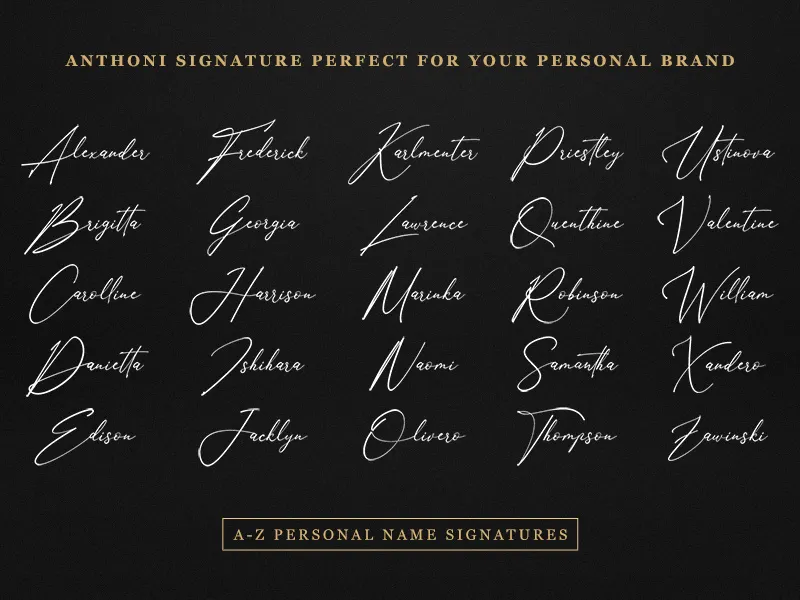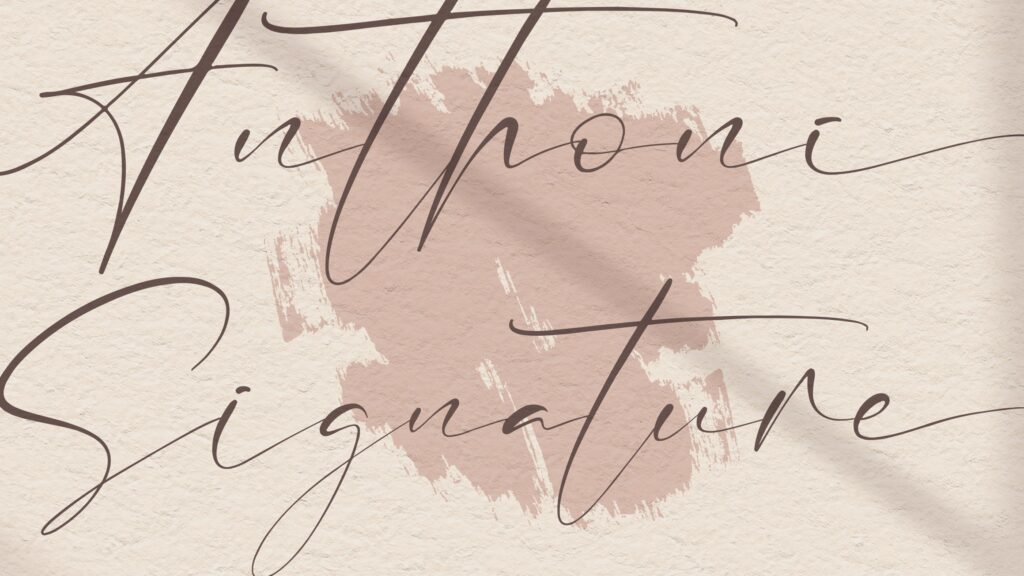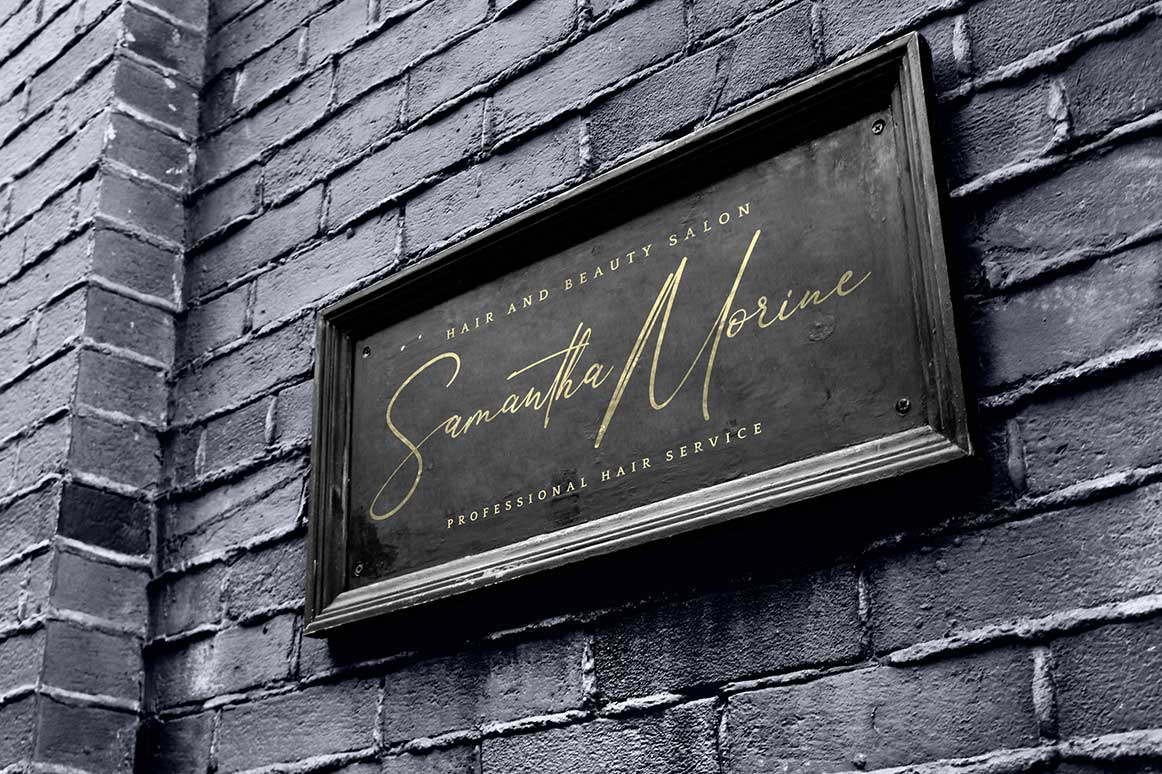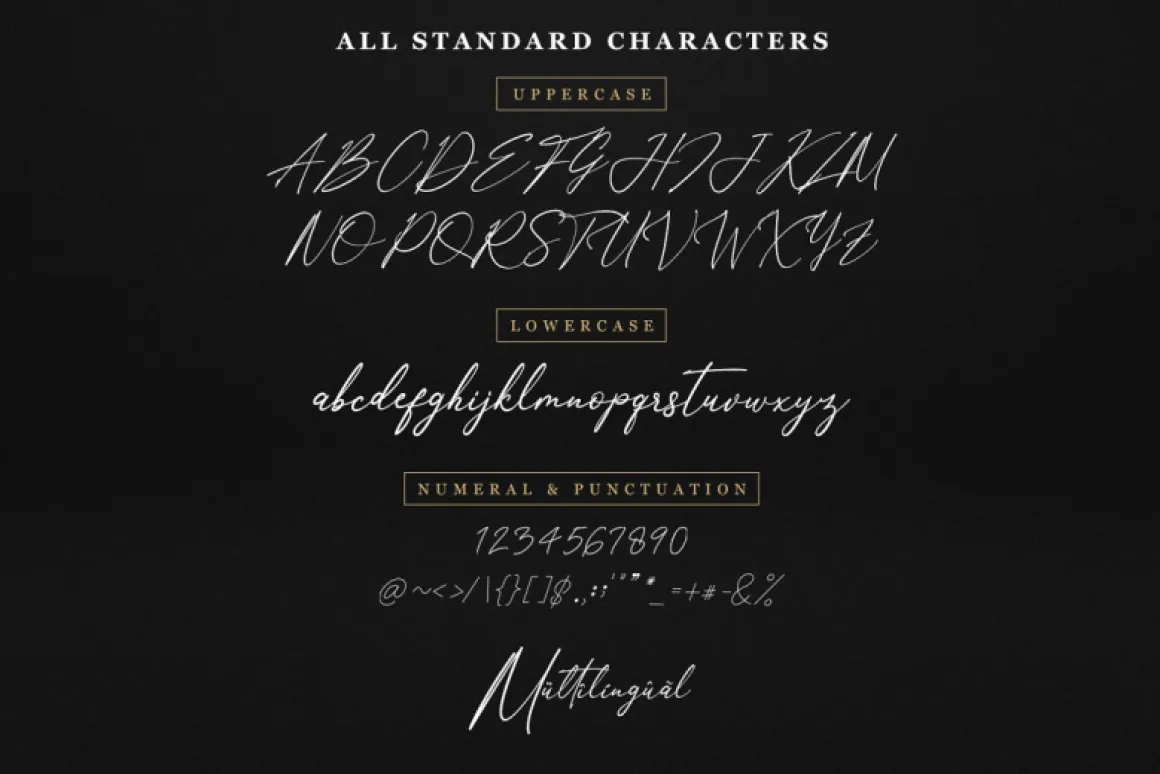
Anthoni Signature Font là bộ phông chữ thuộc dòng Signature Script (chữ ký viết tay) mang phong cách thanh lịch, thượng lưu và tràn đầy cảm xúc tinh tế. Với những đường nét mô phỏng lại nét bút mực lướt nhẹ trên giấy cao cấp, phông chữ này là lựa chọn số một cho các thiết kế logo thời trang nữ, nhãn chai nước hoa, thiệp mời sự kiện VIP và bao bì mỹ phẩm sang trọng. Doozypack.vn cung cấp link tải font Anthoni Signature miễn phí chuẩn kỹ thuật, giúp bạn sở hữu phông chữ chữ ký thời thượng mà không lo gặp bất kỳ lỗi hiển thị dấu thanh nào khi thiết kế in ấn.
Đặc điểm thẩm mỹ độc đáo của bộ font Anthoni Signature
Anthoni Signature không đi theo sự cầu kỳ rườm rà của các dòng thư pháp cổ điển; nó mang đến một ngôn ngữ thị giác đầy tính thời trang đương đại, tự nhiên và giàu cảm xúc.
Phong cách chữ ký cá nhân phóng khoáng và thượng lưu
Đặc trưng lớn nhất của Anthoni Signature Font là cấu trúc nét chữ thanh thoát với độ biến thiên thanh đậm vừa phải. Từng con chữ liên kết với nhau bằng những đường lượn sóng tự nhiên, tạo cảm giác như một chữ ký cá nhân được chấp bút ngẫu hứng nhưng vô cùng nắn nót. Phong cách này mang lại vẻ đẹp quý phái, nữ tính và độc bản, giúp thương hiệu của bạn dễ dàng truyền tải thông điệp về sự chăm chút tỉ mỉ và gu thẩm mỹ cao cấp.
Đường nét uốn lượn tự nhiên với nhịp điệu thanh lịch
Các ký tự của Anthoni Signature Font Việt hóa sở hữu những nét vuốt đuôi dài và các góc chuyển nét mềm mại. Khoảng cách giữa các con chữ được tính toán thoáng đãng, giúp tiêu đề bản thiết kế giữ được sự thanh thoát, sang trọng mà không gây cảm giác rối mắt, cực kỳ ăn ý với xu hướng thiết kế tối giản (Minimalism) trên các ấn phẩm bao bì hiện nay.
Ưu điểm nổi bật của bản Anthoni Signature Font Việt hóa
Khi ứng dụng các phông chữ chữ ký vào thị trường trong nước, sự chỉn chu về dấu câu là yếu tố quyết định đến tính chuyên nghiệp của bản thiết kế:
- Khắc phục triệt để lỗi dấu tiếng Việt: Phiên bản Việt hóa đã được đội ngũ thiết kế trau chuốt thủ công từng dấu câu. Các dấu sắc, huyền, hỏi, ngã, nặng được vẽ thanh mảnh, đặt ở vị trí cân đối so với thân chữ, không gây cảm giác chắp vá hay đè nét làm mất tính thẩm mỹ.